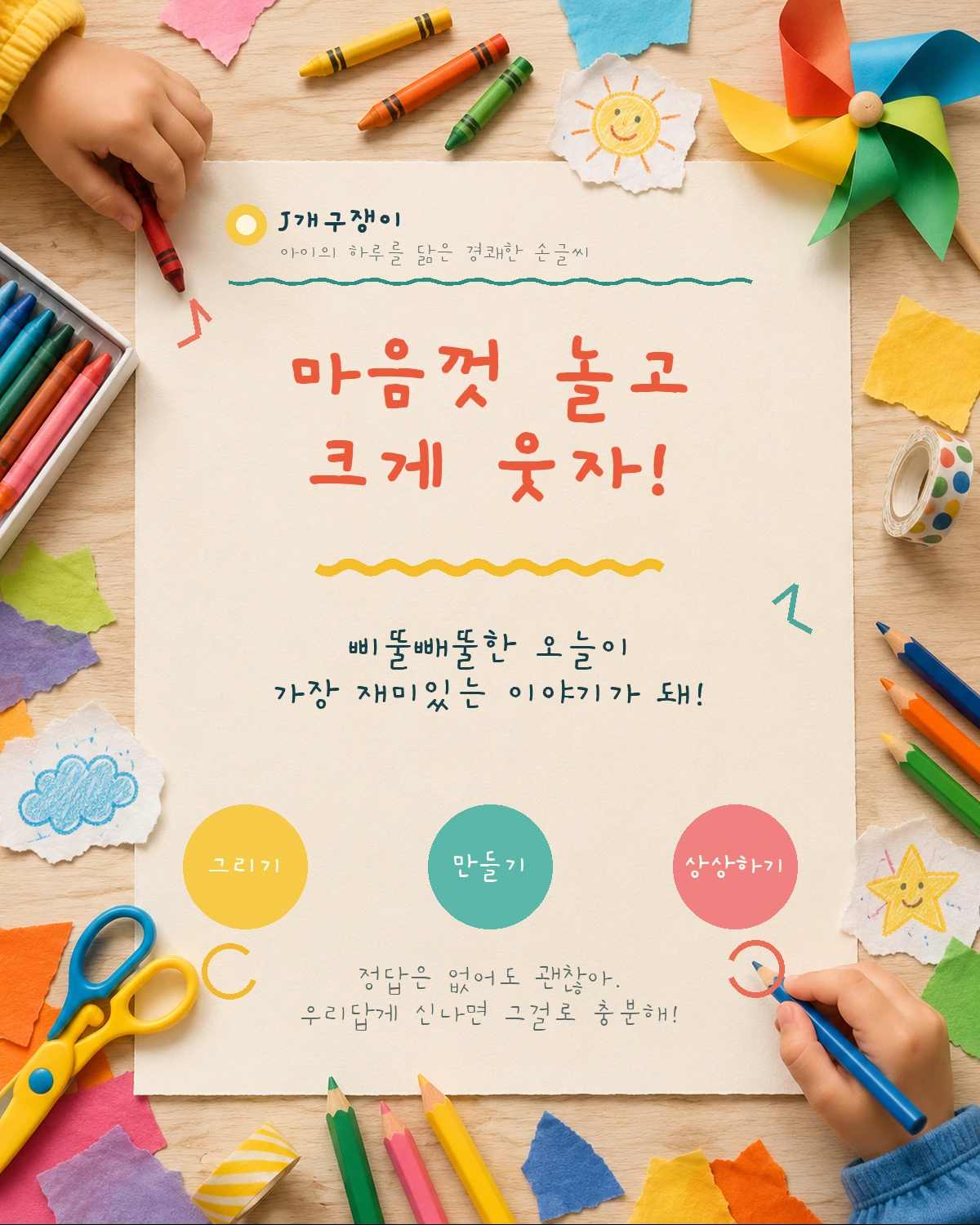
J개구쟁이 무료폰트
J개구쟁이 — 직지소프트에서 배포하는 무료 폰트입니다. 받침이 붙을 때 크게 내려앉는 탈네모틀로, 아이가 쓴 글씨의 경쾌함을 살린 손글씨체
직지소프트가 만들어 2018년 구글폰트에 올린 손글씨 서체입니다. 제작사가 붙인 조형 설명은 따로 찾지 못했고 구글폰트의 소개도 한 줄뿐이라, 아래 형태 이야기는 폰트 파일을 직접 재어 본 것입니다.
받침이 붙을 때 글자가 0.33em이나 아래로 내려가는 탈네모틀입니다. 폰트픽에 올라온 한글 서체 가운데서도 이 차이가 큰 축에 속해, 글줄이 자로 잰 듯 맞지 않고 아이가 공책에 쓴 것처럼 오르내립니다. 가로획이 세로획보다 오히려 굵어서 획이 옆으로 눌린 인상이고, 낱자는 가로로 넓게 퍼져 있습니다.
이 계열에서 드물게 굵기가 Light와 Regular, Bold 세 가지라 손글씨체이면서도 제목과 본문을 굵기로 나눌 수 있습니다. 수록 글자는 완성형 2,350자로 흔한 낱말은 다 나오지만 드문 음절은 빠집니다. 어린이 콘텐츠나 말풍선처럼 손글씨 인상이 필요한 자리에 어울리고 격식이 필요한 문서에는 맞지 않습니다.